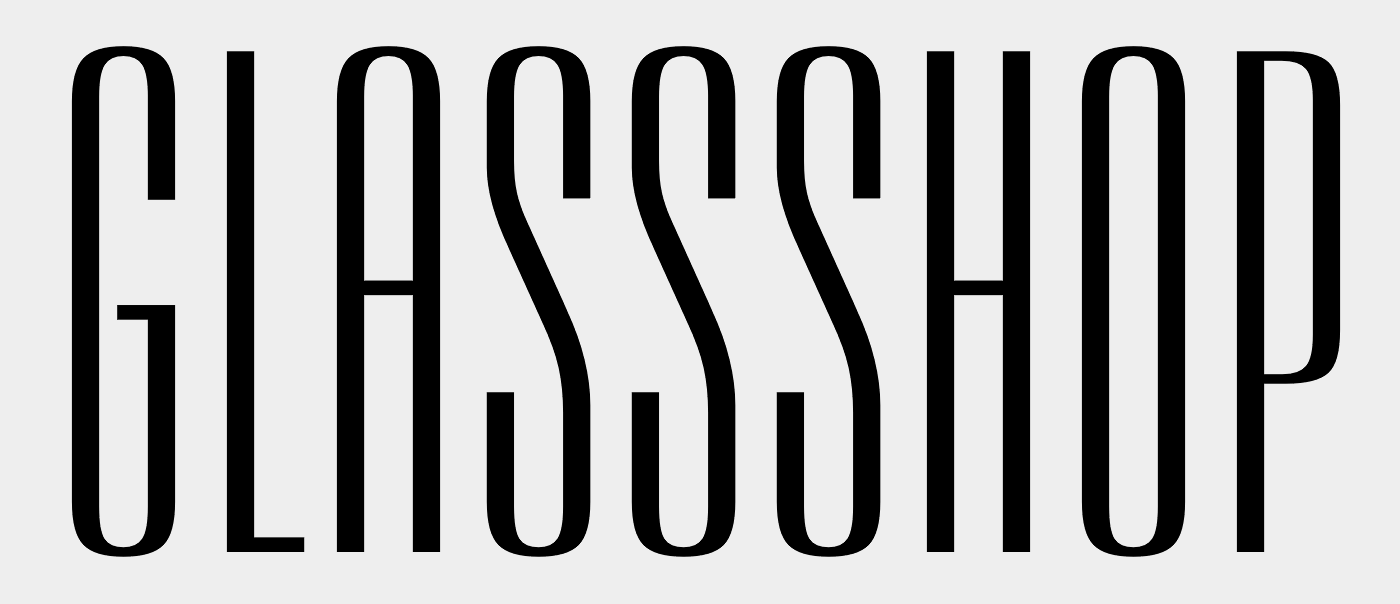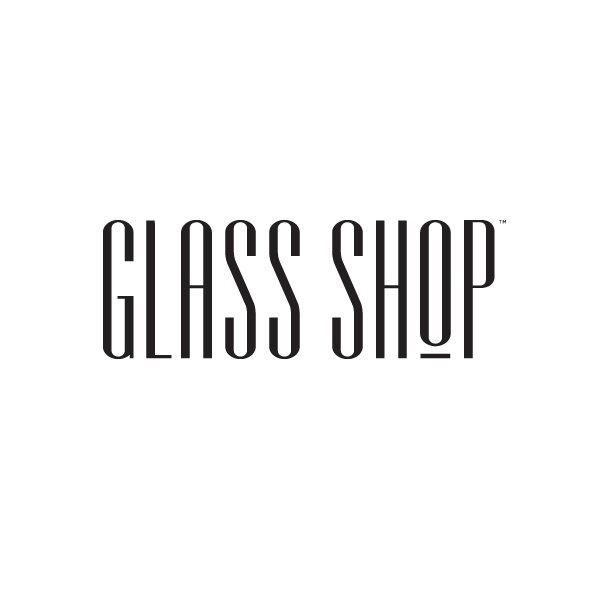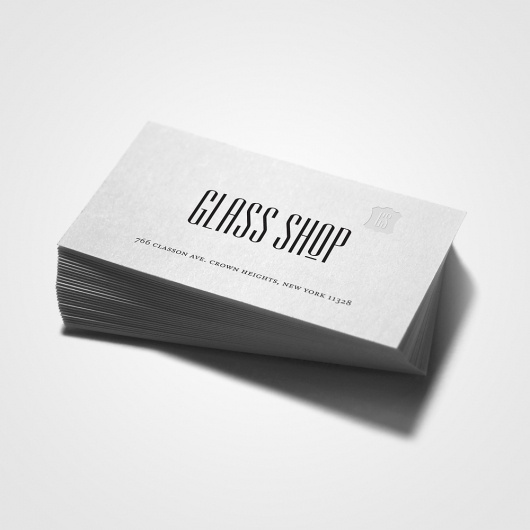
Welche Schrift ist das? (Glass shop)
Ich bin sehr sehr dankbar für jeden Tipp! Es geht um die große Typo "Glass Shop"
Vlt hat ja noch jemand einen Tipp, wo man Schriften suchen und filtern kann!? Bspw nach Sans, sehr schmal und hoch, künstlerisch etc...
Hier unverzerrt:
ich habe jetzt in eigener recherche nur die "Dharma Gothic (Thin)" gefunden. Aber das ist sie auch nicht ganz.
Nachdem das ein Logo ist, liegt die Vermutung nahe, dass das nicht einfach aus einer Satzschrift erstellt wurde.
Ähnlich wäre die Empire …
Ohja! Das sieht schon fast identisch aus! Das G ist am Hals etwas ergänzt worden. Aber ansonsten…